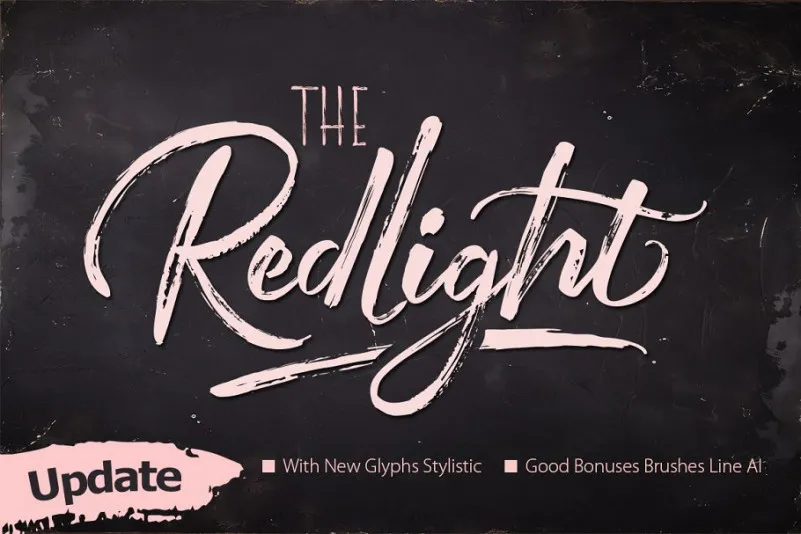
The Redlight Font Duo – Fonte Grátis
The Redlight Font Duo
A The Redlight Font Duo é uma criação inovadora que chega para revitalizar a paleta de opções de fontes no seu projeto. Desenvolvida pelo designer Hamilton, esta Script font combina um ar elegante com um toque moderno e criativo. Especialmente adaptada para inviáveis casamentos, cartões de cumprimento, camisetas personalizadas ou qualquer projeto design que você possa imaginar, a The Redlight Font Duo é uma verdadeira jóia à disposição dos amantes da tipografia. Com uma coleção completa de caracteres padrão, alternativas, pontuação e até mesmo gílos internacionais, esta font oferece um grande potencial para criar designs únicos e memoráveis. Seja você um designer profissional ou iniciante, a The Redlight Font Duo tem algo para complementar seus projetos. Em um mundo de milhões de opções de fonts disponíveis, o que torna essa font tão especial é justamente sua personalidade única e seu valor como uma ferramenta poderosa no seu arsenal criativo. Descubra o brilho da The Redlight Font Duo hoje!